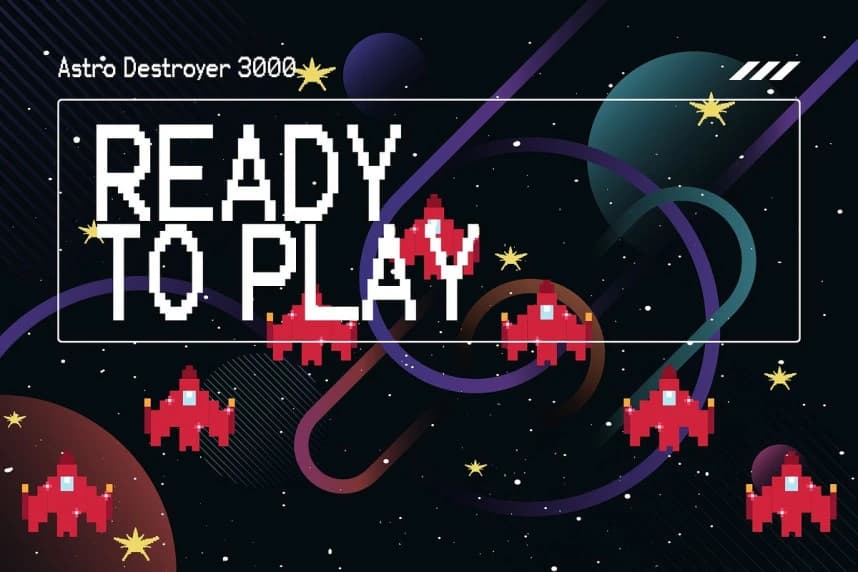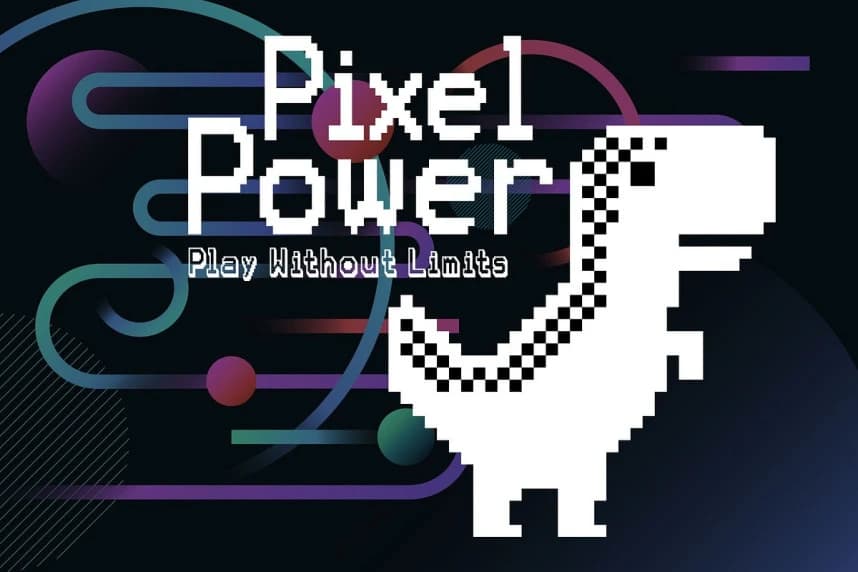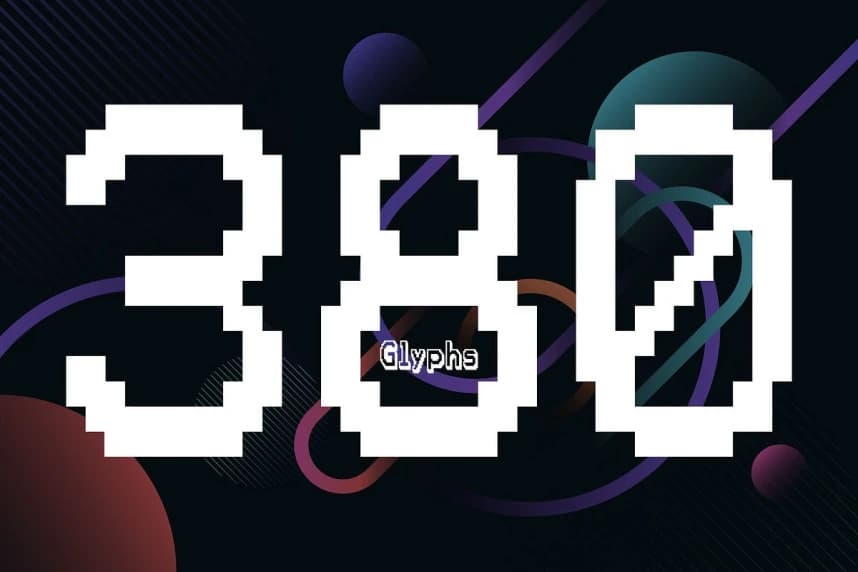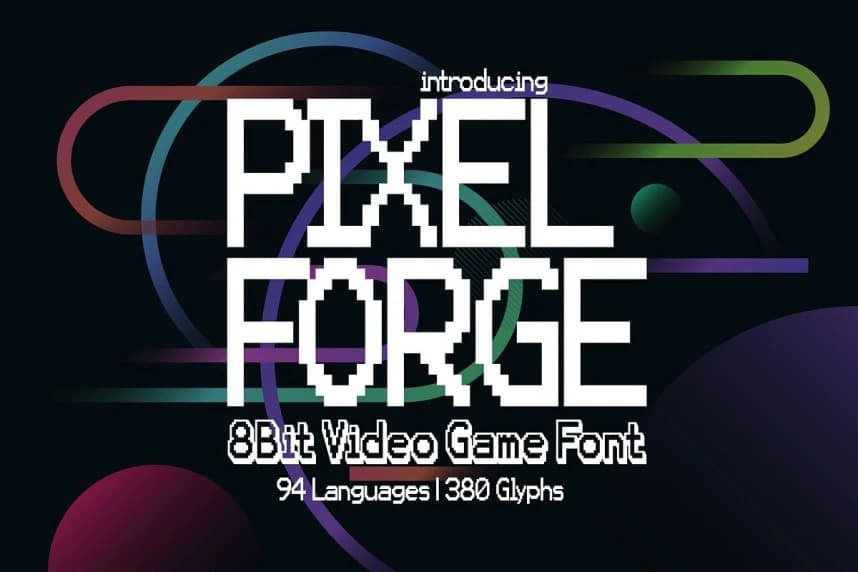
Pixel Forge Font, retro hassasiyeti modern derinlikle seven yaratıcılar için tasarlanmış cesur, ızgara üzerine kurulu bir piksel gösterim yazı tipidir. Temiz piksel geometrisiyle üretilmiş ve güçlü bir 3D sürümüyle eşleşmiş olan bu yazı tipi, hem nostaljik hem de fütüristik tasarımlar için anında et
Pixel Forge Font, retro hassasiyeti modern derinlikle seven yaratıcılar için tasarlanmış cesur, ızgara temelli bir piksel gösterim yazı tipidir. Temiz piksel geometrisinden oluşmuş ve güçlü bir 3D sürümüyle birleştirilen bu yazı tipi, hem nostaljik hem de geleceğe yönelik tasarımlar için anında etki sağlar.